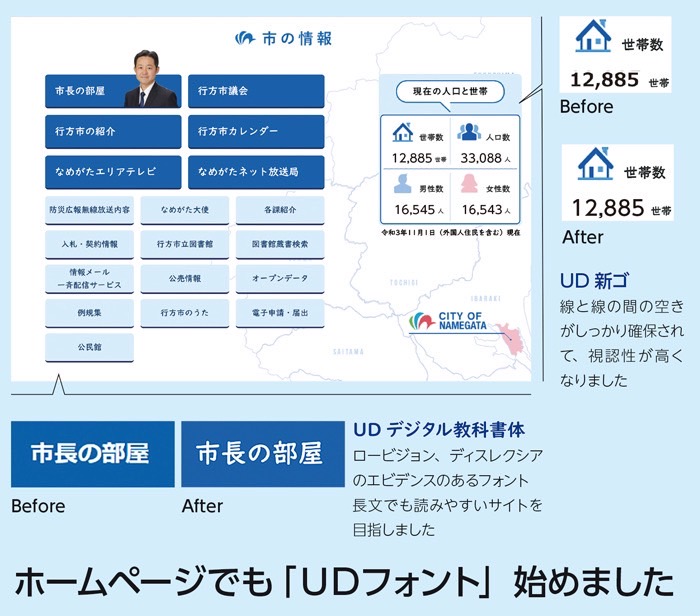
茨城県行方市が茨城県内自治体初となるホームページにユニバーサルデザインフォントを導入
茨城県行方市は、誰一人取り残さない情報発信を実現すべく、12月1日(水)から市のホームページに、茨城県内自治体では初めて(当市調べ)、UD(ユニバーサルデザイン)フォントを導入したことを発表した。
ユニバーサルデザインフォントを導入の背景
ユニバーサルデザインフォントを導入の背景として、茨城県行方市では、市の広報誌は平成29年から職員PCの環境では平成31年からUDフォントを採用し、市民や市からの文字情報をより多くの方々が正しく取得できるように環境を構築。
採用フォント(書体)について
今回、採用したUDフォントは、年齢や障害の有無、個々の能力差などにかかわらず、多くの人々が利用しやすいように「ユニバーサルデザイン」の思想が文字に込められた株式会社モリサワのUDフォントを採用した。
見出しや、タブ、ボタンなどにはUD新ゴ。
本文にはUDデジタル教科書体を採用。
サイト フォント比較(行方市ホームページから)
▼フォント変更前
▼フォント変更後
採用フォント(書体):「UD新ゴ(見出し、タブ、ボタン)」の特長
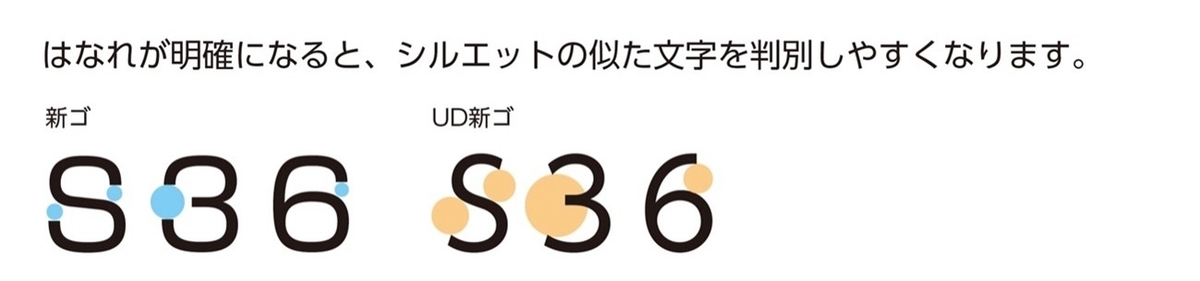
文字の形がわかりやすく、読み間違えにくい
UD新ゴは、駅名表示やサイン、成分表、取扱説明書など多くの印刷物で使われてきた新ゴというフォントをユニバーサルデザイン化したフォント。
そのため、目に馴染みのある文字でありながら、幅広い層の方々に認識しやすく、さまざまな画面の大きさでも、わかりやすい文字情報となる。
採用フォント(書体):「UDデジタル教科書体(本文)」の特長
読みやすさ・読みの速度のエビデンスを備えたUDフォント。
書き方の方向や点・ハライの形状を保ちながらも、太さの強弱を抑え、ロービジョン(弱視)、ディスレクシア(読み書き障害)に配慮したデザインの教科書体。
ロービジョン(弱視)、ディスレクシア(読み書き障害)を対象とした「読みやすさ」の検証や、ディスレクシア(読み書き障害)を対象とした「読みの速度」に関する検証で、比較書体より読みやすく、読みの速度に改善があることが証明された書体となる。
▼一対比較法を用いた評価画面(縦書き:国語)
今後について
行方市では、「誰一人取り残さない情報発信」と「情報のユニバーサルデザイン化」の実現を目指し、さまざまなシーンでUDフォントを活用していく動きをさらに強化していく予定とのこと。